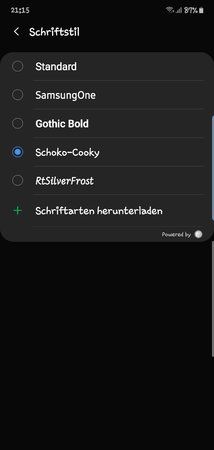
Schriftart ändern
Hallo, gibt es wirklich keinen Weg, außer Root, die Schriftart zu verändern? Im Speicher gibt es ja den Ordner Fonts, konnte aber leider bisher nichts damit erreichen.
2 Schriftarten gibt's ja immerhin. Finde beide auch recht schick
Du willst die Systemschrift ändern! Keine Ahnung. Wird aber wohl ohne Root kaum möglich sein.
Ich finde nicht mal den fonts Ordner.
Muss aber zugeben, dass mir die oneplus slate gut gefällt. Wenn auch etwas groß. So ähnlich hätte ich sie wohl auch gewählt.
Kann man den themes nachinstallieren? Weil die Stelle der Einstellung für die Schrift wirkt so, als ob andere themes auch eine andere Schrift mitbringen könnten.
Aber @zaph hat doch in seinem Post einige Vorschläge gemacht. Waren das alles Vorschläge mit Root?
. Wenn auch etwas groß. So ähnlich hätte ich sie wohl auch gewählt.
Einstellungen - System - Bedienungshilfen
Da lässt sich die Schriftgröße oder auch die gesamte Anzeigegröße verkleinern.
@Kuli11 das ist mir bewusst. Aber auch auf ganz klein ist die slate immer noch viel größer als die andere Schriftart, roboto oder wie die heißt. Ist halt einfach ein größerer font bzw hat evtl auch mehr zwischenraum zwischen den Zeichen.
Sieht man ja auch in der Vorschau der Schriftarten, das werden mehrere Zeilen mehr
Mit Ausnahme von Handys mit Miui-Android kenne ich kein Gerät, bei dem sich die Systemschrift ohne Root ändern ließe. Das war so bei all meinen Samsungs wie auch beim Oneplus 2.
@toscha42 Wie kommst Du darauf?
Bei Samsung lässt sich die System Schriftart ohne Probleme ändern. Ab Werk stehen zwei oder drei zur Auswahl. Via Galaxy Store lassen sich etliche downloaden. Das ging bei Samsung schon immer und ich hatte auch nie die Empfindung das dies etwas besonderes ist.
Das war dann ungeschickt ausgedrückt. Ich meinte natürlich, eigene Fonts zu installieren, die lokal als .ttf vorliegen. Das ging zumindest beim Galaxy S4 wie auch beim Tab S, meine letzten Samsung-Geräte, nur mit Root.